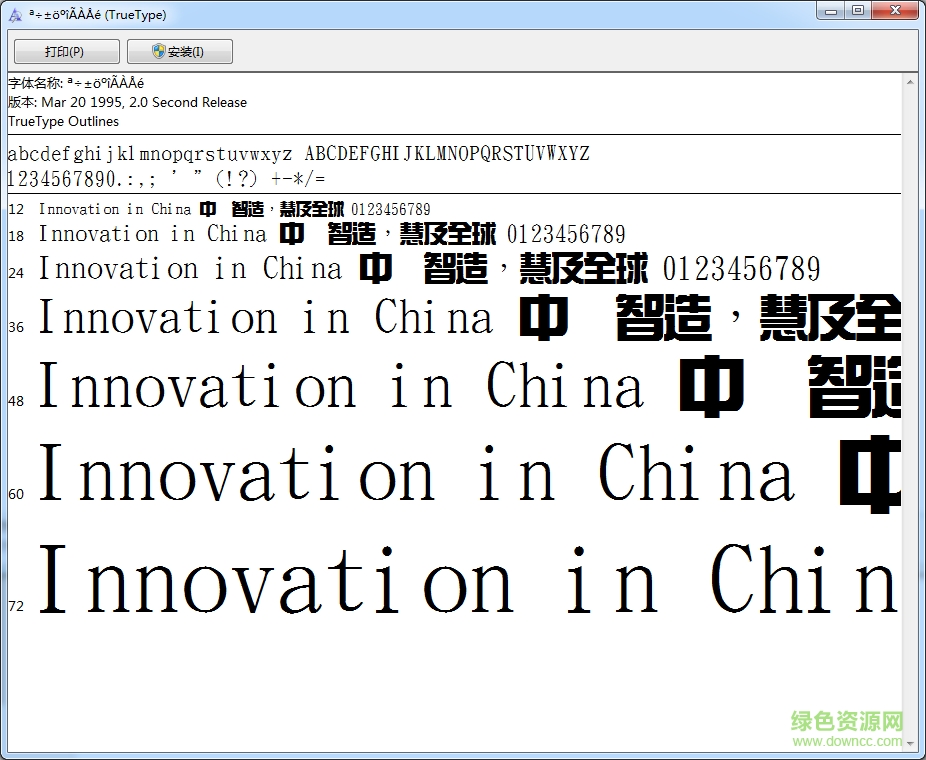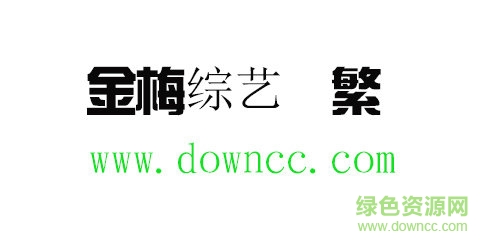
金梅綜藝體繁是一款金梅字體中的繁體電腦字體軟件,字體大氣清秀,以繁體顯示彰顯個性,是書法家們經(jīng)常用于創(chuàng)作的字體之一,如果你想設(shè)計一個有特色的廣告,也可以選擇這款字體實驗一下,說不定就能達到意想不到的效果哦,感興趣的朋友就來本站下載使用吧!
金梅綜藝體繁是一款應(yīng)用于設(shè)計方面的簡體中文漢字,該字體大方得體,字形進行了加粗加長處理,整體效果十分出色,可以用于包裝印刷、簽名設(shè)計、電影字幕、圖形設(shè)計等領(lǐng)域,有喜歡的朋友可免費下載收藏。